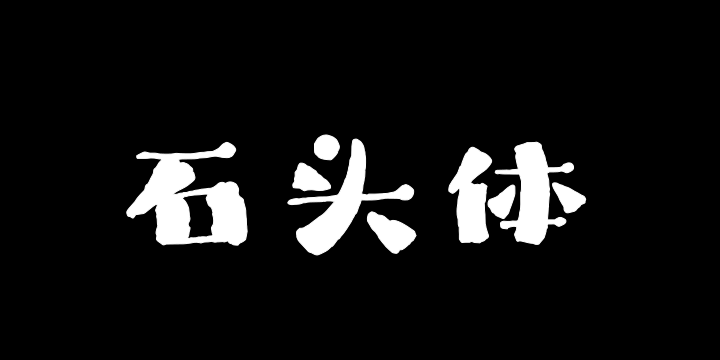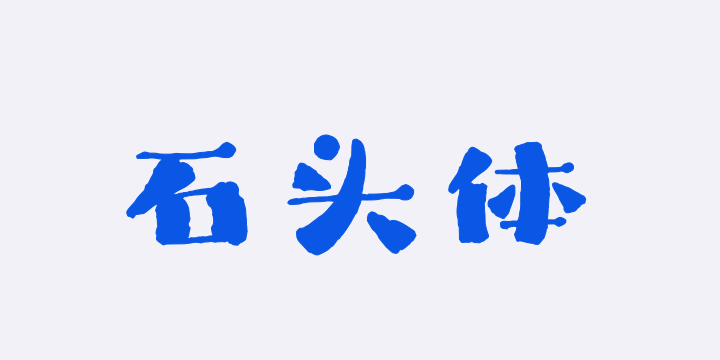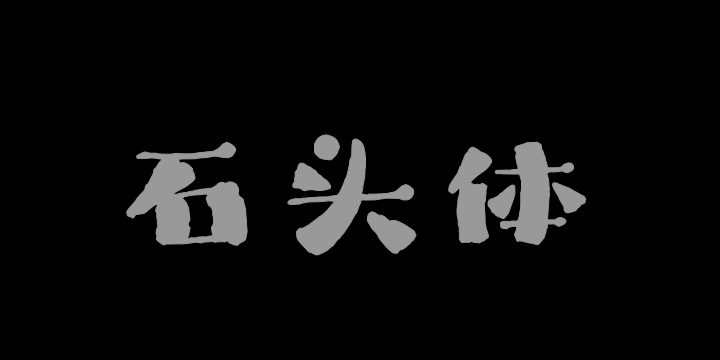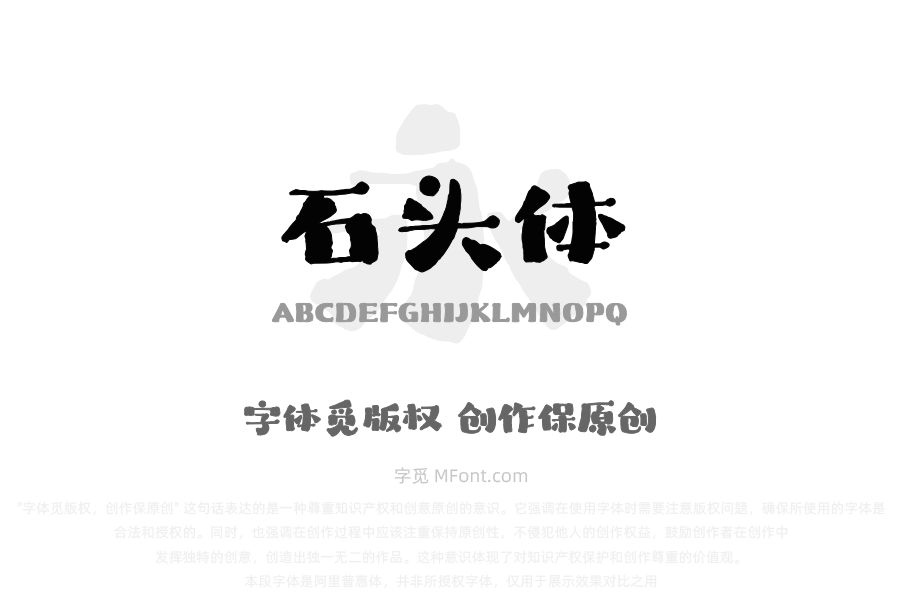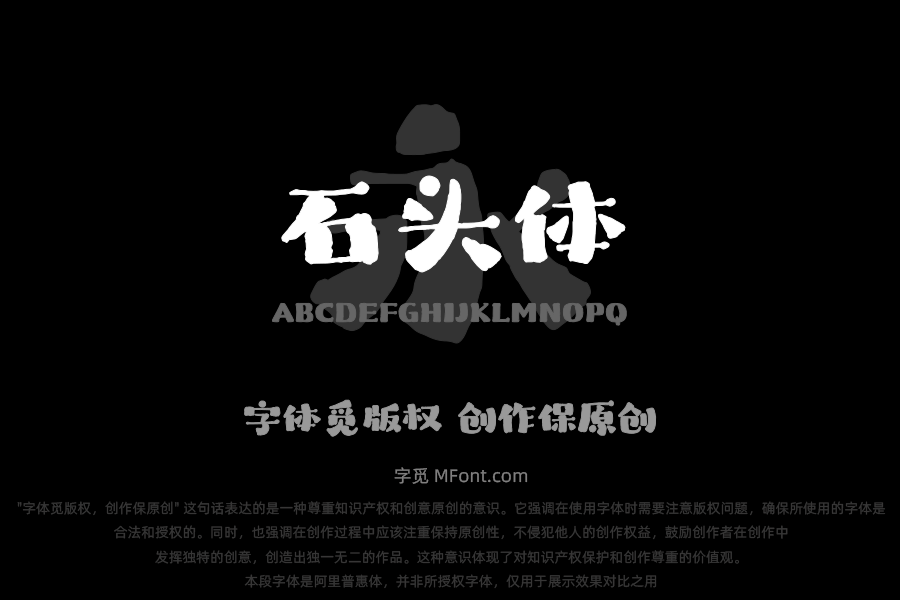
字体全名: 上首石头体
字体简介: 上首石头体,笔画以厚重敦实为基底,边缘保留不规则的 “崩石痕迹”—— 起笔收笔处或钝涩、或带细微缺口,转折处隐现凿刻的力度变化,模拟石材受锤击后自然形成的肌理。字体结构摒弃标准化的对称与均匀,融入手写书法的疏密错落与动态韵律:部分偏旁部首刻意 “错位”,笔画排布时松时紧,仿若石匠依石材天然形态顺势雕琢的随性,让厚重的字体不失灵动生气,避免机械感。适用于搭配标志、广告标语、商业广告等高端属性。